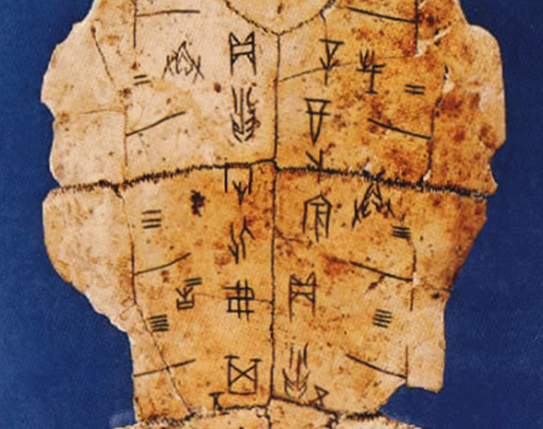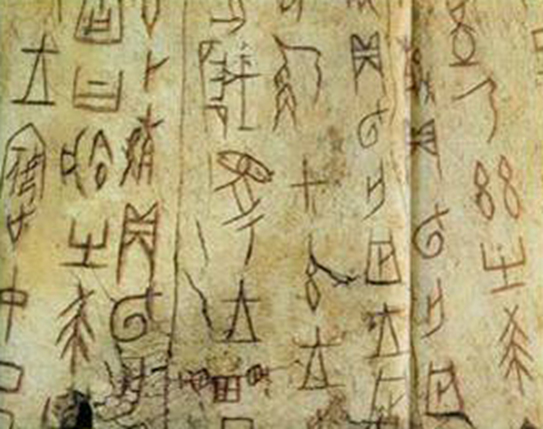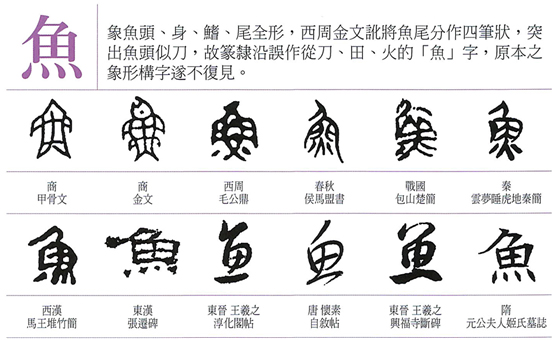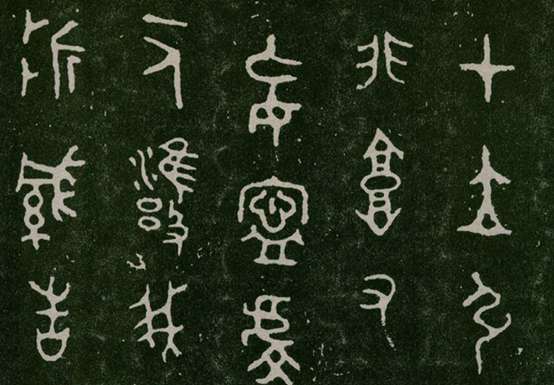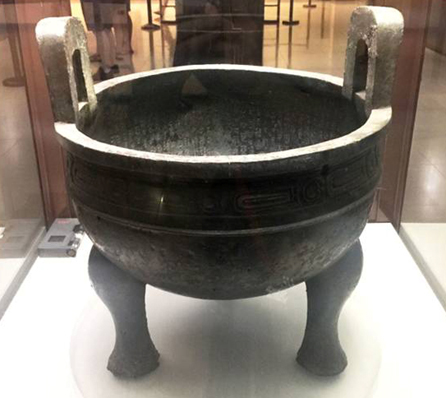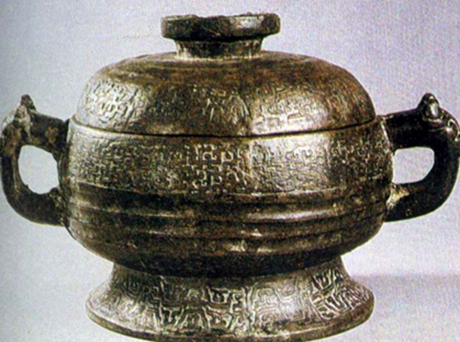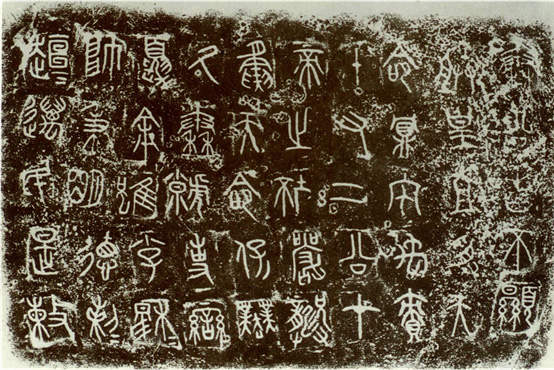
汉字文化圈印刷字体的渊源与发展探讨(一)
在印刷字型产业浸淫27年,见证了台湾从DOS时代,计算机造字开始的印刷字型产业的发展。我们经历了临摹、累积、创作,整个成熟的过程,全新设计已不具挑战性,文鼎想创造的是未来设计。
近几年电子阅读逐渐凌驾于纸本阅读,汉民族所原创的明/宋体汉字印刷字体,逐渐因为电子化阅读的时代趋势,而逐渐淡出我们的眼球,因此文鼎深觉有必要针对越来越多的电子智能阅读,设计全新的明/宋体,在思索与寻找中,第一个发想便是溯源,研究明/宋体的发源与演化,希望能以文字造形为核心,来探讨其时空背景、科技环境、应用需求下印刷字型的设计本质,以寻找设计的方向。
从2014年起文鼎团队就系统的搜集古籍善本图档及印刷史研读,将一篇篇文字叙述,进行书籍搜集及其图档年代排序,并进行造型研究,我许多假日常是在书案前,图书馆中渡过,虽是笨鸟慢飞,却也逐步拼接出属于中文/汉字印刷字体造型发展的脉络。
探讨印刷字体,在根本上就离不开『印刷』与『字体』,而汉字印刷字体,更是来自于书写的书体。在印刷术还未发明前,书籍都凭抄写而来,因此中国书法的字体,就成为书籍内容的丰沛字体来源,书法的博大精深,不是我可谈论的,我仅仅搜集一些代表文物,从印刷物的观点来欣赏其中的文字造型,从这些脉络中观察其演化的本质。
汉字发展史上无论是用毛笔书写、契刻或者铸造方式,出现书体大致共有12体(如上图,出处:故宫图书_趣味甲骨金文)。从最早出现的甲骨文,距今3,600年 (1,600BC~1,066BC);到最晚出现的楷书,距今也都有1,850年 (151~230年),都具有悠久的历史。我搜集了一些代表性文物,而其中的文字都跟其承载器物的制造目的、材质、制造方法息息相关,以下我们依出现年代逐一欣赏:
其中我要特别介绍约制作于公元前770年的『秦公簋』铭文
盖有铭文54字,器身有铭文51字,共105字,许多学者认为是使用方块印模法,制字模时一一打就,字字连续印成,然后浇铸,乃活字印模压印的活字印刷鼻祖,如下图片我们可看到一些重复出现的文字,都具有同样的造型,可印证其为印模打就,可说是启活字印刷之先河(参考『秦公簋:秦人重器出秦源』;『秦公簋铭文研究』)。
但亦有其他学者从科技验证,认为铭文是以硬笔书法方式制作(参考『论先秦青铜器铭文之制作- 有关“漏铅法”的一点证明』)
无论是以何方式制作,整篇铭文字体规范严谨,已具备了印刷文字基本可读性的设计精神。